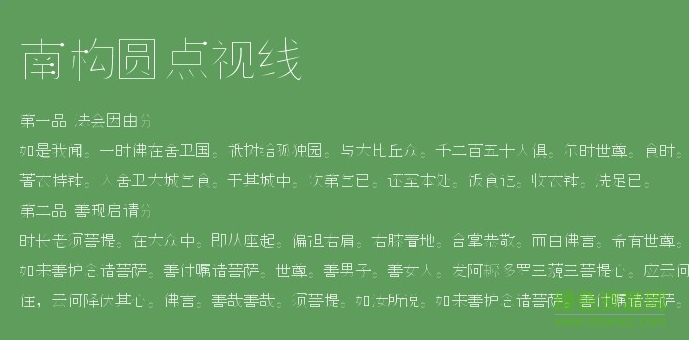
葉根友南構(gòu)圓點(diǎn)視線
南構(gòu)圓點(diǎn)視線字體是一款葉根友類休閑圓點(diǎn)風(fēng)格字體,字體橫筆畫結(jié)尾處都有一個(gè)圓點(diǎn),非常的有特點(diǎn),整體效果別有一番韻味,更多好看字體盡在綠色資源網(wǎng)!
南構(gòu)圓點(diǎn)視線是一款內(nèi)文特色字體,應(yīng)用線條和圓點(diǎn)的創(chuàng)意來設(shè)計(jì)。字與字之間一氣呵成,清晰簡(jiǎn)約脫俗,故取名南構(gòu)圓點(diǎn)視線。
該字體盡顯南構(gòu)圓點(diǎn)視線的柔情,字體筆畫相互連接,有一種輕描淡寫的韻味,非常的文雅好看,是葉根友字體里面比較大方得體的了。